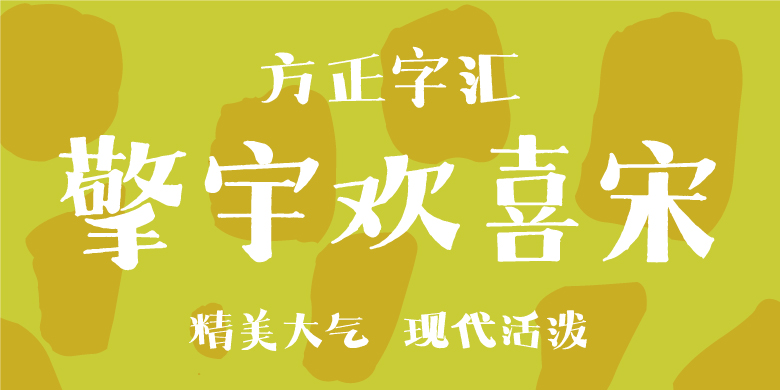
方正字汇-擎宇欢喜宋
宋体,是为适应印刷术而出现的一种汉字字体。笔画有粗细变化,常用于书籍、杂志、报纸印刷的正文排版。长久商业书法书写对创作欢喜宋也是一种启发,既保留了宋体的精美大气,又呈现出现代活泼感;文字是因为记录、阅读而产生,它传播给人以信息;它是一个文明传承的载体,代表每个人的审美观;它不是沉默的物品,而是蕴涵情感的。
字体设计正处于一个特别美好的时代。